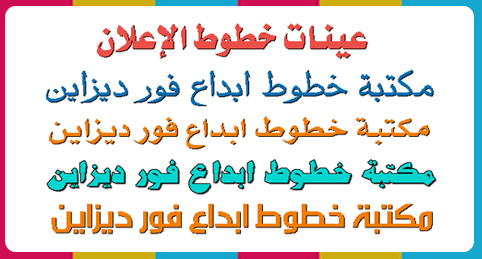
نبذه تعريفيه عن خطوط الإعلانات والعناوين
خط الإعلان أو خطوط الإعلانات والعناوين كما هو واضح من تسميتها هي مجموعه من أرقى الخطوط العربيه
والتي تستخدم في التصاميم الإعلانيه والترويجيه سواء إعلانات الويب للمواقع والمنتديات
أو إعلانات الصحف والجرائد والمجلات والكتب
أو إعلانات الدعايه والإعلان وكافة المطبوعات الدعائيه والترويجيه
ويتميز خط الإعلان بالجمال الفني بالإضافه للجديه والوضوح وسهولة القراءه
ومواصفات ومميزات الخط تجعله الاختيار الأول لكل مصمم
وخط الإعلان مميزاته تجعل منه إسم على مسمى شكلاً ومضموناً .
عينه من خطوط الإعلان